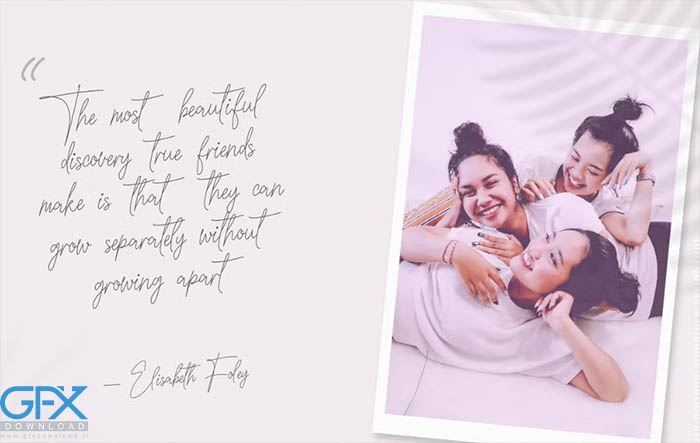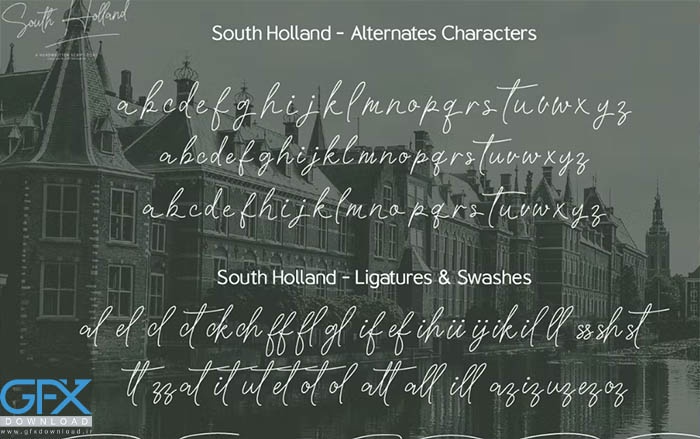
فونت انگلیسی رایگان South Holland
در این پست با معرفی رایگان فونت جدید South Holland Signature font یک فونت انگلیسی اسکریپت با طراحی دستخط شیک و زیبا با شما همراه هستیم. فونت انگلیسی South Holland با حروف بزرگ، کوچک، اعداد و علائم نگارشی استاندارد آمده است. همچنین شامل نویسه‌های Alternates با حروف کوچک، لیگاتورهای استاندارد، و swashes بود.
فونت South Holland Signature font کاملاً برای نقل قول‌های دست‌نویس، آرم‌های به سبک امضا، دعوت‌نامه، پروژه‌های برندسازی شیک، و طرح‌های محصولات و لوازم التحریر دست‌ساز.